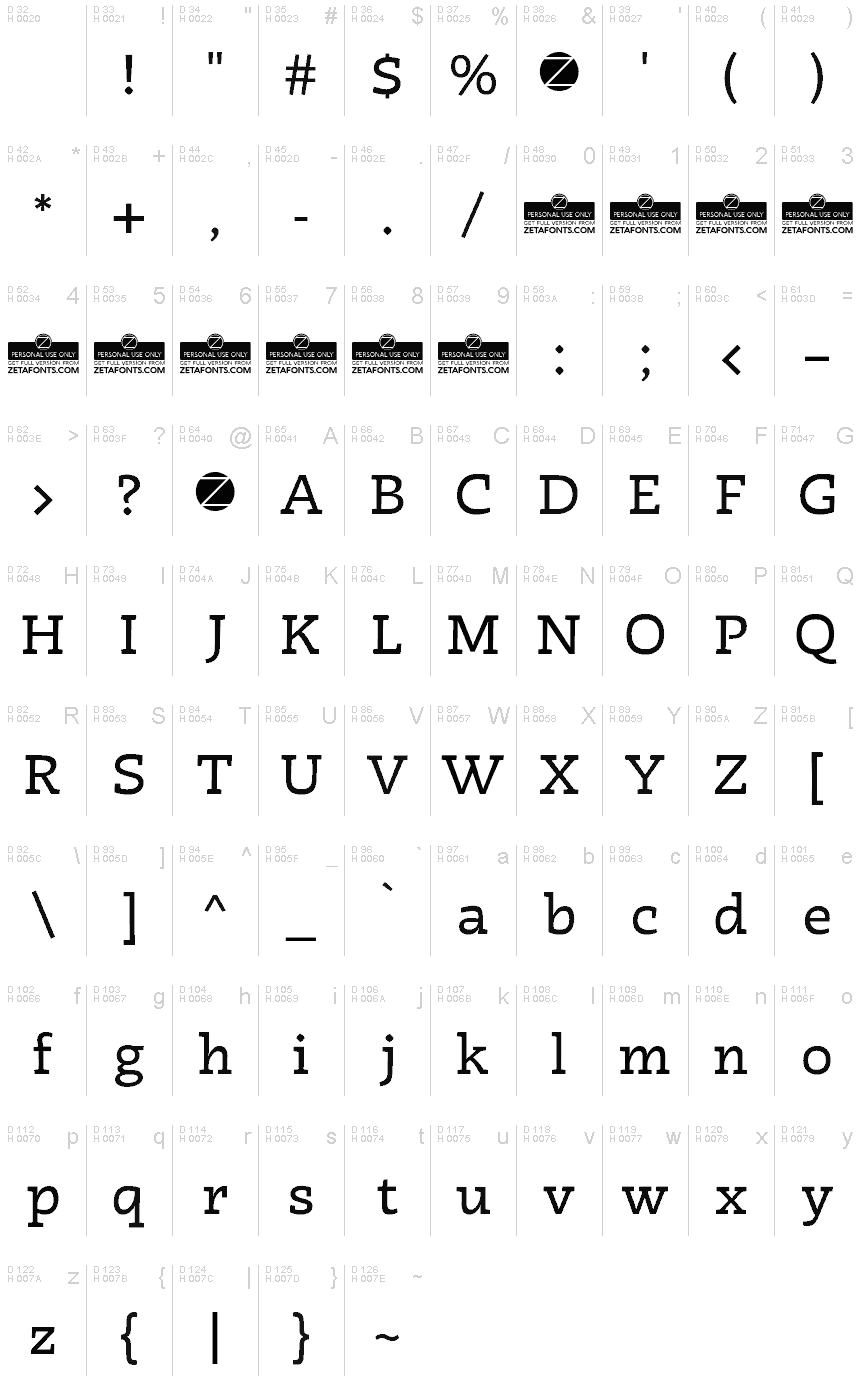
عائلة خطوط Radcliffe، التي صممها كوزيمو لورنزو بانشيني وأندريا تارتاريللي في عام 2018، هي إعادة ابتكار لتصميمات Clarendon التقليدية بحثاً عن مظهر "كلاسيكي معاصر". صُمم خط Radcliffe ليمنح طابعاً من الأناقة، ويتميز بزوائد قوية، ومحور عمودي، وتباين منخفض، وهي سمات Clarendon، ولكنها مصقولة بلمسة إنسانية ومنهج خطي يظهر جلياً في الخطوط المائلة.
صُمم Radcliffe في المقام الأول كخط للعناوين (Display) مع مجموعة واسعة من الأوزان المضبوطة بدقة للاستخدامات التحريرية وتصميم الشعارات. كما تم تعزيز العائلة بخط Radcliffe Text، الذي طُوّر بخمسة أوزان مع ارتفاع أكبر للحروف الصغيرة (x-height) ونسب أكثر تكثيفاً قليلاً، مما يسمح بأقصى درجات الوضوح في النصوص الطويلة على الويب وبأحجام صغيرة.
تتضمن العائلة أيضاً وزنين فريدين من Radcliffe Casual، صُمما بجمالية تباين معكوسة، مما يجعلهما مثاليين لأنشطتك الترفيهية. تدعم جميع خطوط Radcliffe ميزات OpenType الكاملة مع بدائل أسلوبية، وربط اختياري للحروف، وأشكال أرقام موضعية، وأشكال مزخرفة (في الخطوط المائلة)، بالإضافة إلى دعم كامل لأكثر من 70 لغة تستخدم الأبجدية اللاتينية والسيريلية.
Radcliffe Casual